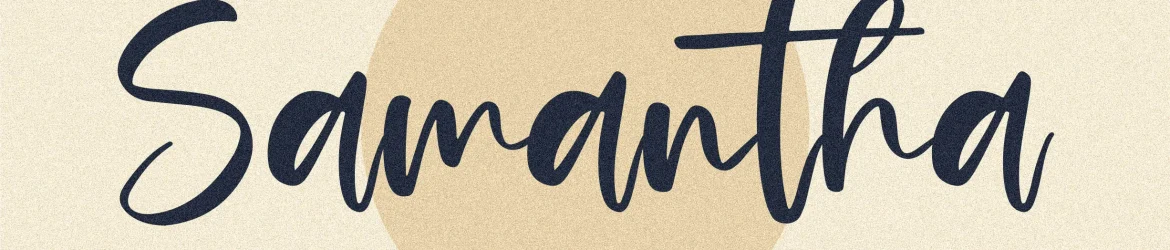
Samantha Font – Download Grátis
A ‘Samantha Font’ é uma elegante fonte escrita à mão que se destaca em projetos diversos, desde criação de logotipos e identidade visual até design de embalagens de produto e materiais promocionais como adesivos, mala d’Itália, e revistas. Suas linhas delicadas e movimentos naturais criam um toque autêntico que combina perfeitamente com a decoração de chá em tigelas personalizadas ou em uma caixa de papelão para presentear alguém especial. Seja uma mensagem de homenagem, um convite de casamento, uma capa de livro ou até mesmo o recado da sua próxima festa temática, a ‘Samantha Font’ oferece uma aparição autêntica e imediatamente reconhecível. Aqui na categoria de fontes escritas à mão, você encontrará mais opções que são verdadeiras obras de arte, idealmente projetadas para ajudar a enriquecer qualquer projeto gráfico em progresso.